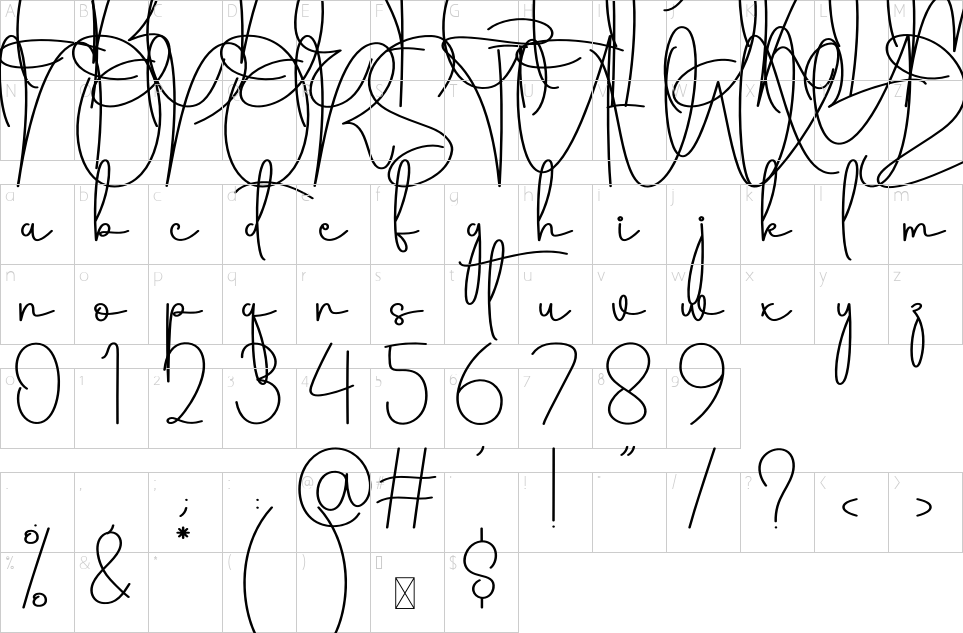
A fonte Photography Font, disponível aqui na categoria de Fontes Grátis, é uma escolha perfeita para quem quer agregar um toque de elegância à sua fotografia digital. Desenvolvida por William Jhordy, esta fonte é perfeitamente compatível com os sistemas operacionais Windows e Mac, permitindo-lhe personalizar e estilizar seu trabalho de fotografia de forma única e impactante. Afinal, um bom designer sabe que a escolha da fonte pode fazer toda a diferença no resultado final. Com apenas 321 downloads, você pode adquirir esta fonte de alta qualidade sem ter que pagar uma fortuna. Em uma era cada vez mais digital, Photography Font é a escolha certa para aqueles que querem expressar sua criatividade de forma clara e poderosa. Descubra a sua versão agora e deixe sua fotografia falar por si mesma.